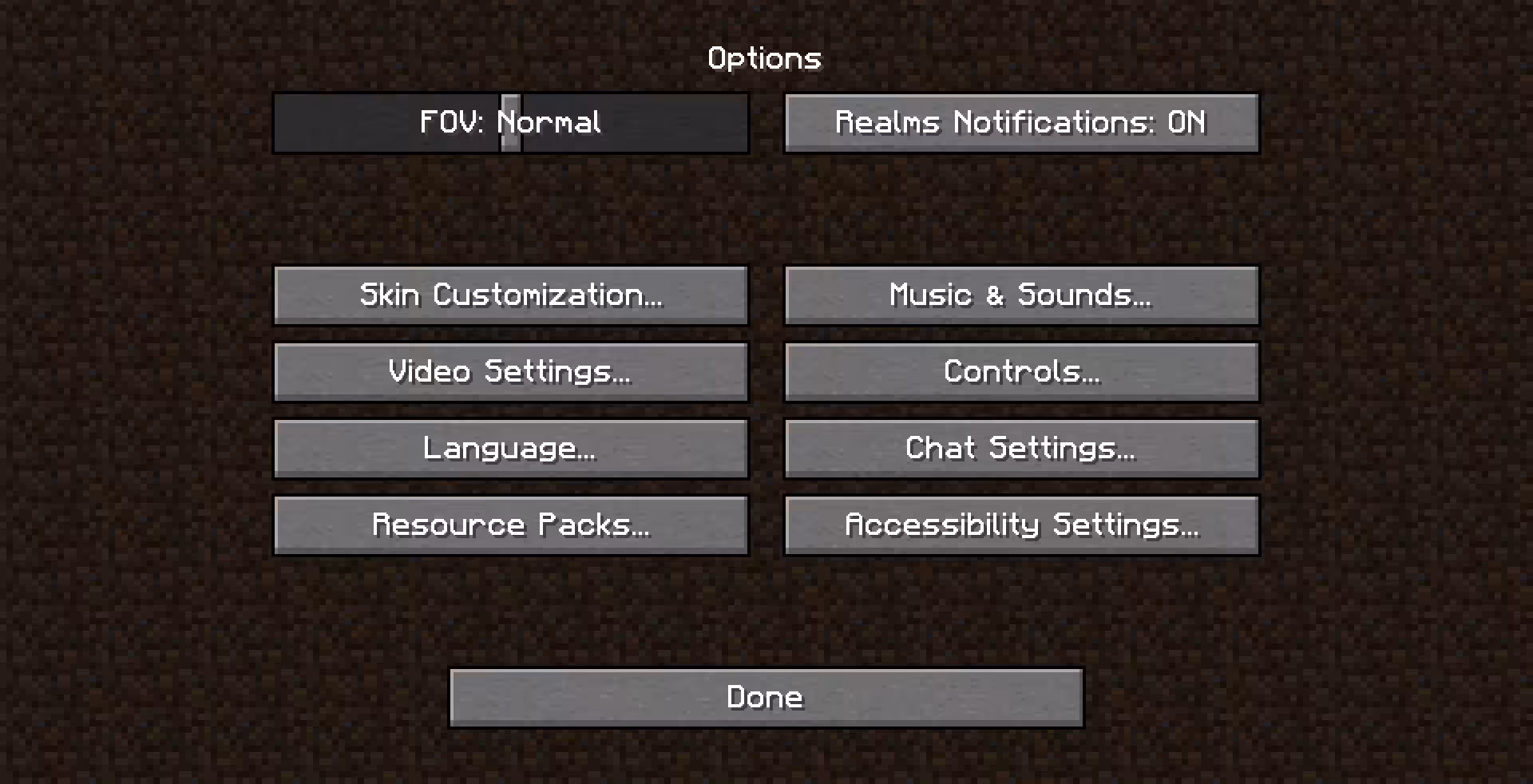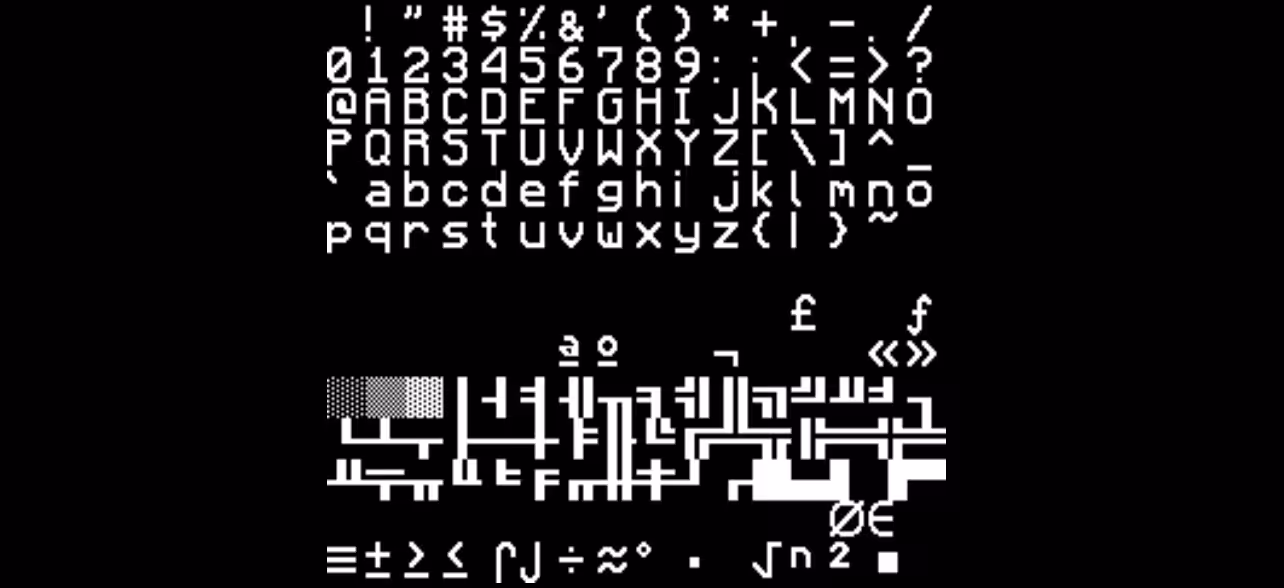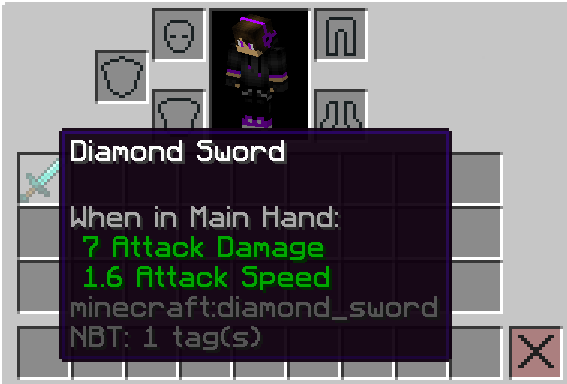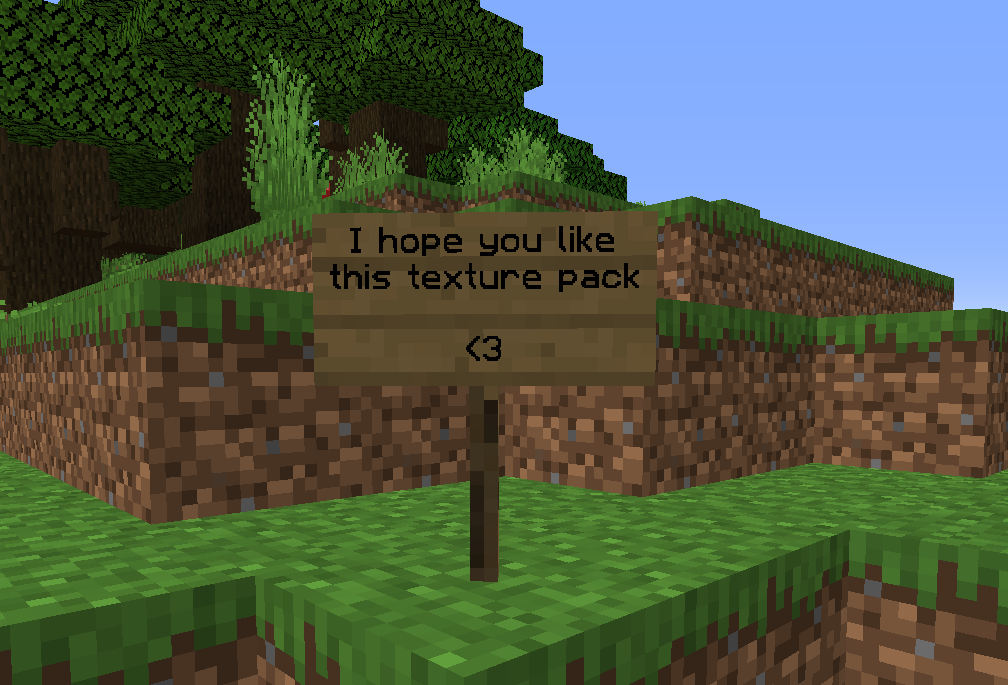
[Resource Pack] Smooth Font [1.8.9 – 26.2]
Pack de textures : Smooth Font
Vous trouvez que la police d’écriture de Minecraft est parfois un peu désordonnée ou difficile à lire ? Le pack de textures Smooth Font est un add-on pour compléter un pack de textures qui vise à rendre la police de caractères de Minecraft plus agréable à lire. Que ce soit pour les noms d’éléments, les dialogues, les chiffres ou toute autre forme de texte dans le jeu, ce pack permet d’apporter une touche de clarté, idéale pour ceux qui trouvent les polices par défaut trop rudimentaires ou pixelisées.
Ce pack est basé sur le Faithful, connu pour son approche détaillée et réaliste tout en restant proche du style classique de Minecraft. Cependant, Smooth Font se différencie en ne modifiant que la police d’écriture, sans toucher au reste des textures du jeu. Cela permet d’avoir une amélioration ciblée qui se concentre sur la lisibilité, tout en préservant l’esthétique du jeu.